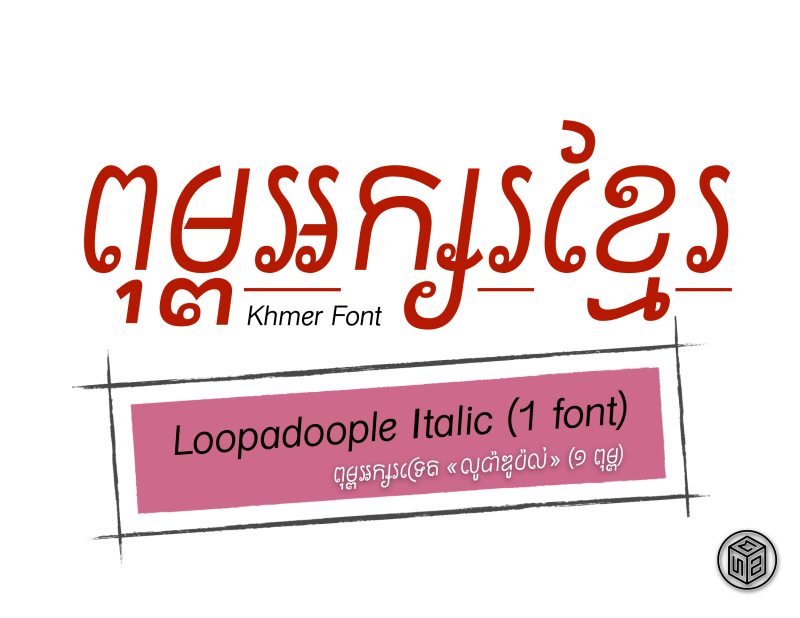
Loopadoople Loopy [Single] Italic (1 font)
Single download file of the classic san serif style Khmer font - Loopadoople Italic
Loopadoople គឺជាពុម្ពអក្សរខ្មែរ Opentype ដែលត្រូវបានរចនាឡើងជាពិសេសឱ្យប្រើការសរសេរនូវ ស្លាកផលិតផល ចំណងជើងធំ ផ្លាកសញ្ញាហាង និង ការផ្សាយពាណិជ្ជកម្មដើម្បីបង្កើនយីហោទំនើបឱ្យកាន់ប្រសើរ។
រចនាប័ទ្មនេះគឺល្អសម្រាប់ប្រយោគខ្លី ឃ្លាតូចៗ ឬក៏ពាក្យពីរបីដែលនឹងប៉ះពាល់ដល់អារម្មណ៍ និងសេចក្តីរីករាយ - ដូចជាការបរិភោគបង្អែមត្រឹមតែបរិមាណតិចតួច ពុម្ពអក្សរនេះគឺល្អសម្រាប់ការអានពាក្យខ្លី។
Loopadoople is an Opentype Khmer font that was designed specifically​ for product labels, large titles, shop signs, and advertisement to enhance modern branding.
This style is ideal for short sentences, small phrases, or few words that will impact mood and joy - just like eating desserts in small amounts, this font is excellent for reading short words.